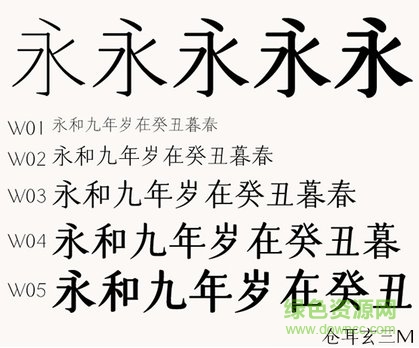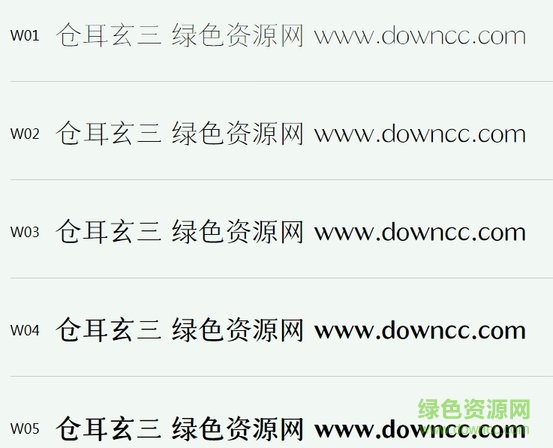
蒼耳玄三是一款端方大方的系列字體,包括倉(cāng)耳玄三01、倉(cāng)耳玄三M兩個(gè)字體,每個(gè)字體均含有五種不同的表達(dá)方式,給人不同程度的選擇,讓文字更有傳達(dá)效果,喜歡的朋友就來(lái)綠色資源網(wǎng)下載吧!
倉(cāng)耳玄三是一套大家族字庫(kù),有01、M兩個(gè)方向,玄三01現(xiàn)代端莊,玄三M古樸大氣,各有W01 W02 W03 W04 W05五個(gè)字重,可以滿(mǎn)足不同場(chǎng)景和媒介的應(yīng)用。
倉(cāng)耳玄三01
倉(cāng)耳玄三01家族字庫(kù)是創(chuàng)新型的正文字體,在筆形弧線(xiàn)的平滑處理使字體看上去圓潤(rùn)飽滿(mǎn)。這款字體集合了楷體的結(jié)構(gòu)、宋體的筆形、黑體的粗細(xì)比例的優(yōu)點(diǎn),字體風(fēng)格新穎,閱讀更為舒服。
倉(cāng)耳玄三M
這是一套創(chuàng)新性的家族字庫(kù),在結(jié)構(gòu)上借鑒了明代宋體高挑緊湊的字型結(jié)構(gòu),在筆形上選用了倉(cāng)耳字庫(kù)特有的玄三筆形,上演了一部字體的穿越劇,讓古代與現(xiàn)代、時(shí)間與空間完美融合。
玄三家族字庫(kù),是我在央美讀研期間,畢業(yè)創(chuàng)作的一部分。是在書(shū)寫(xiě)的基礎(chǔ)上,集楷、宋、黑三種字體的優(yōu)點(diǎn),針對(duì)正文字體的一種創(chuàng)新性探索。